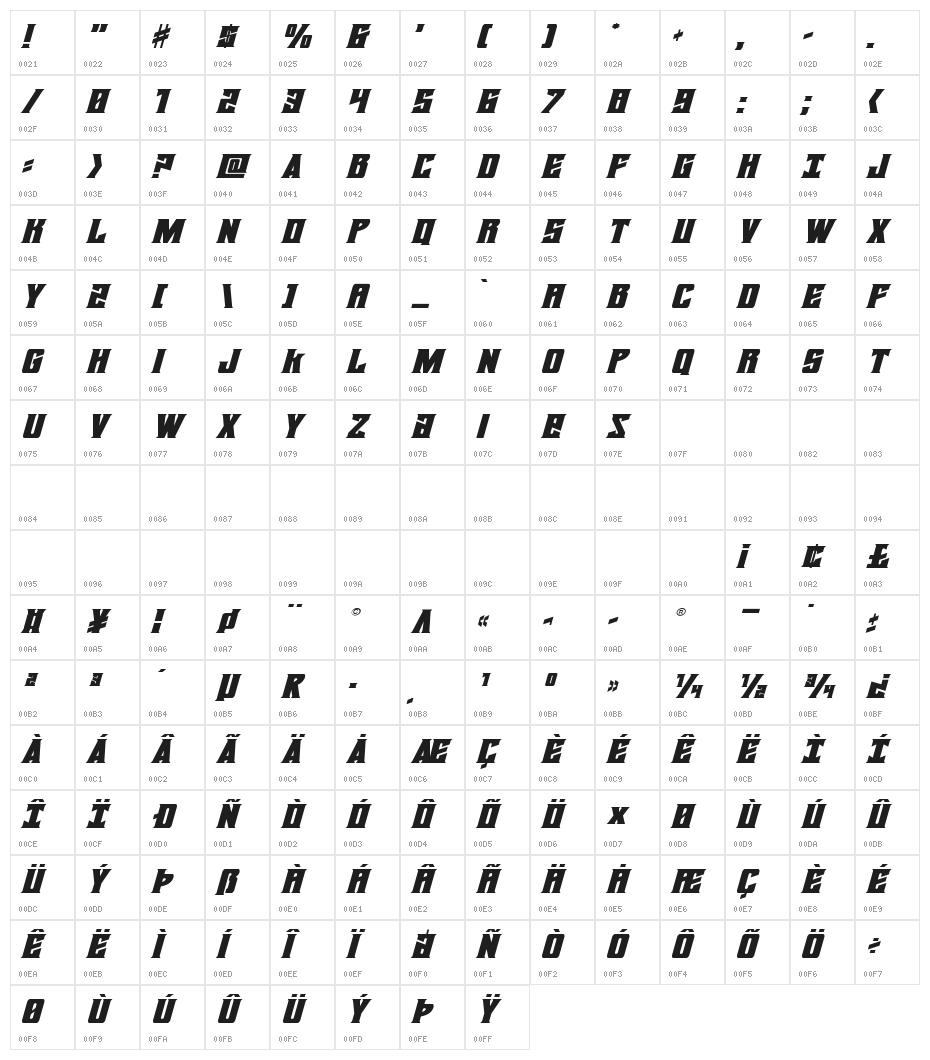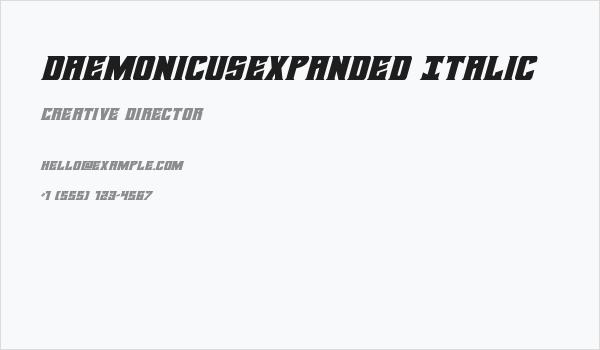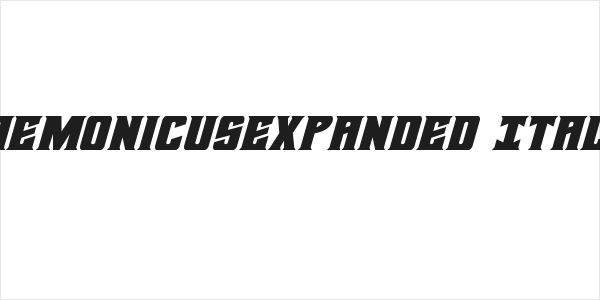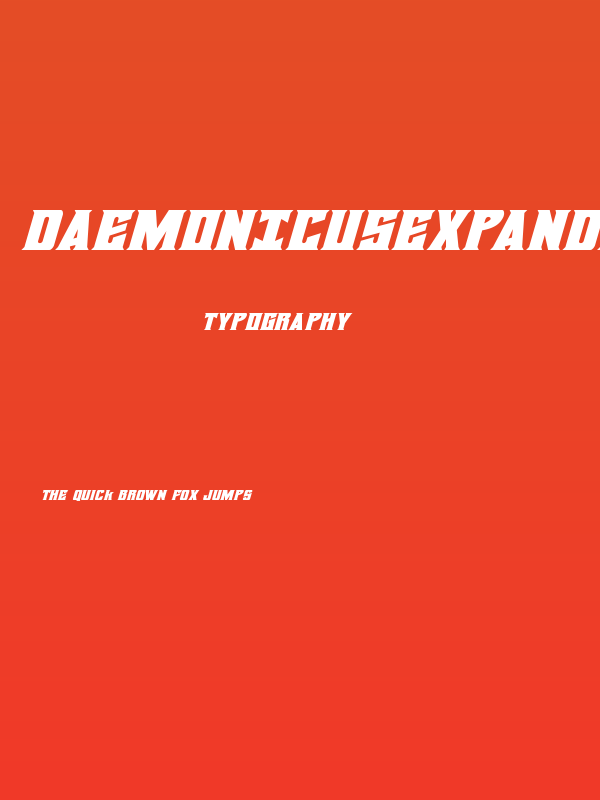
DaemonicusExpanded Italic Font
✎ Thick
| Gewicht | Expanded Italic |
| Kategorien | Thick |
| Breite | Expanded |
| Vorgeschlagene Projekte | Perfect for sports branding, action movie posters, video game titles, and dynamic advertising campaigns. |